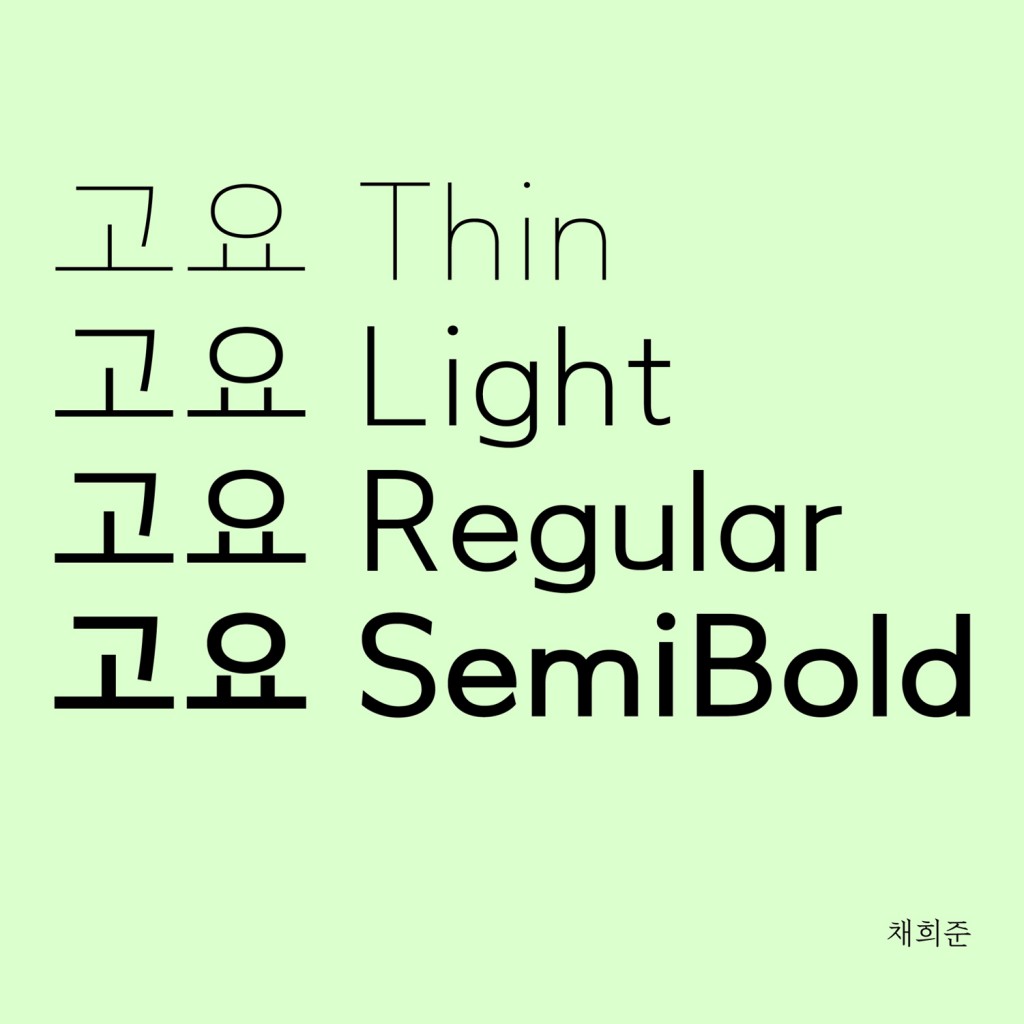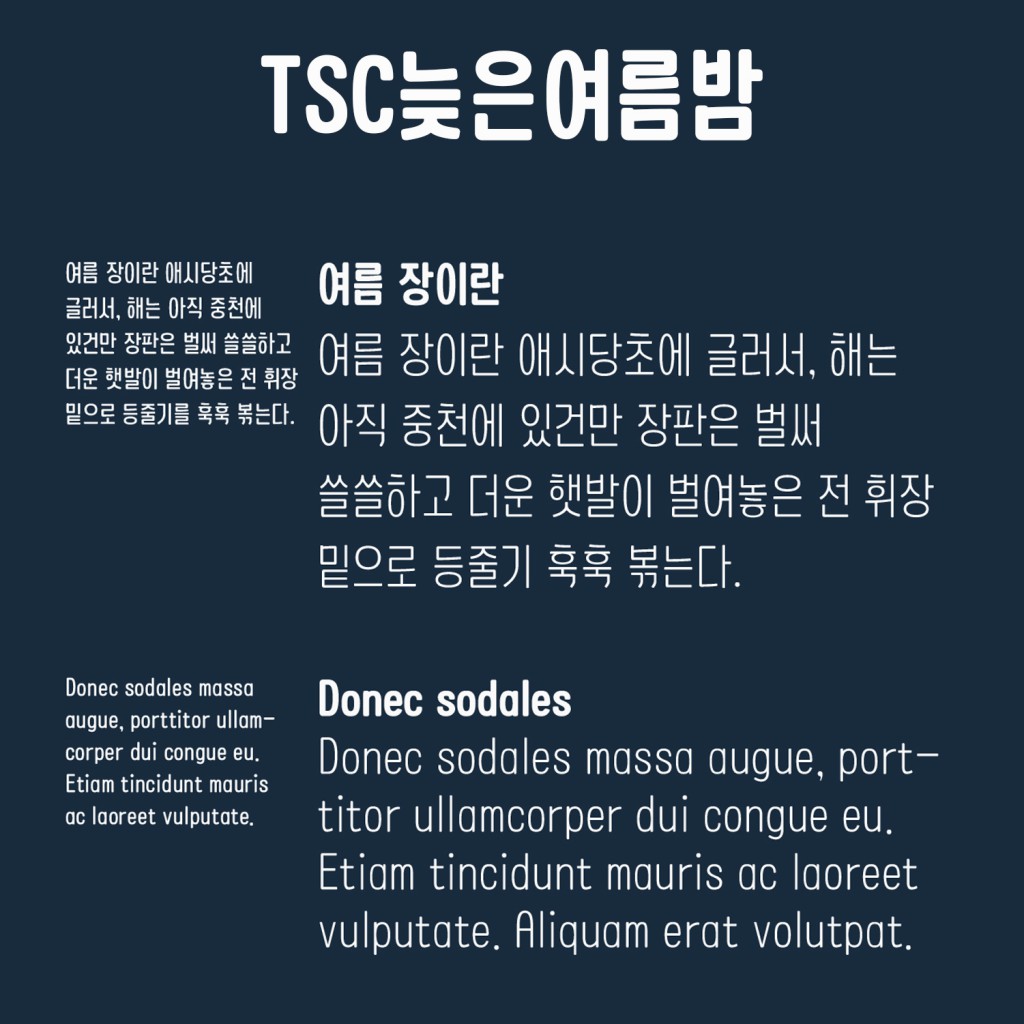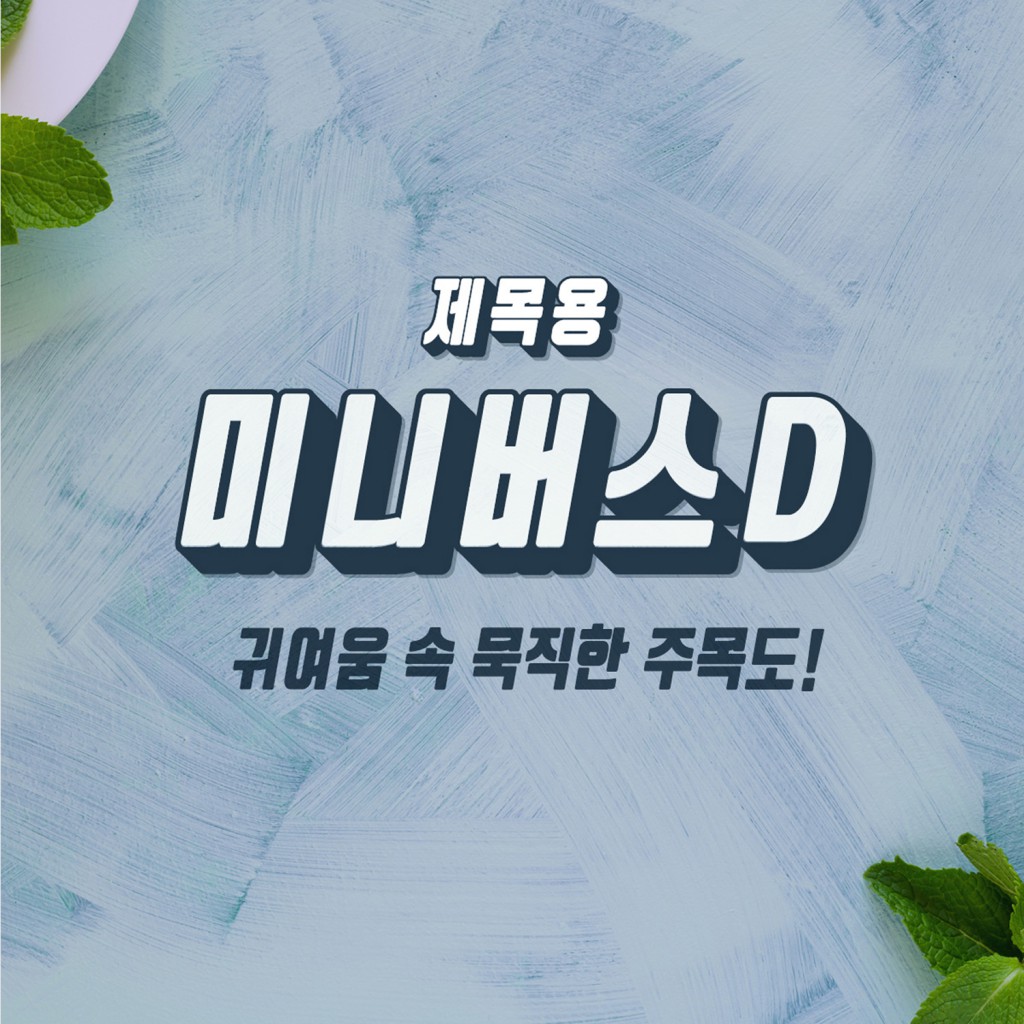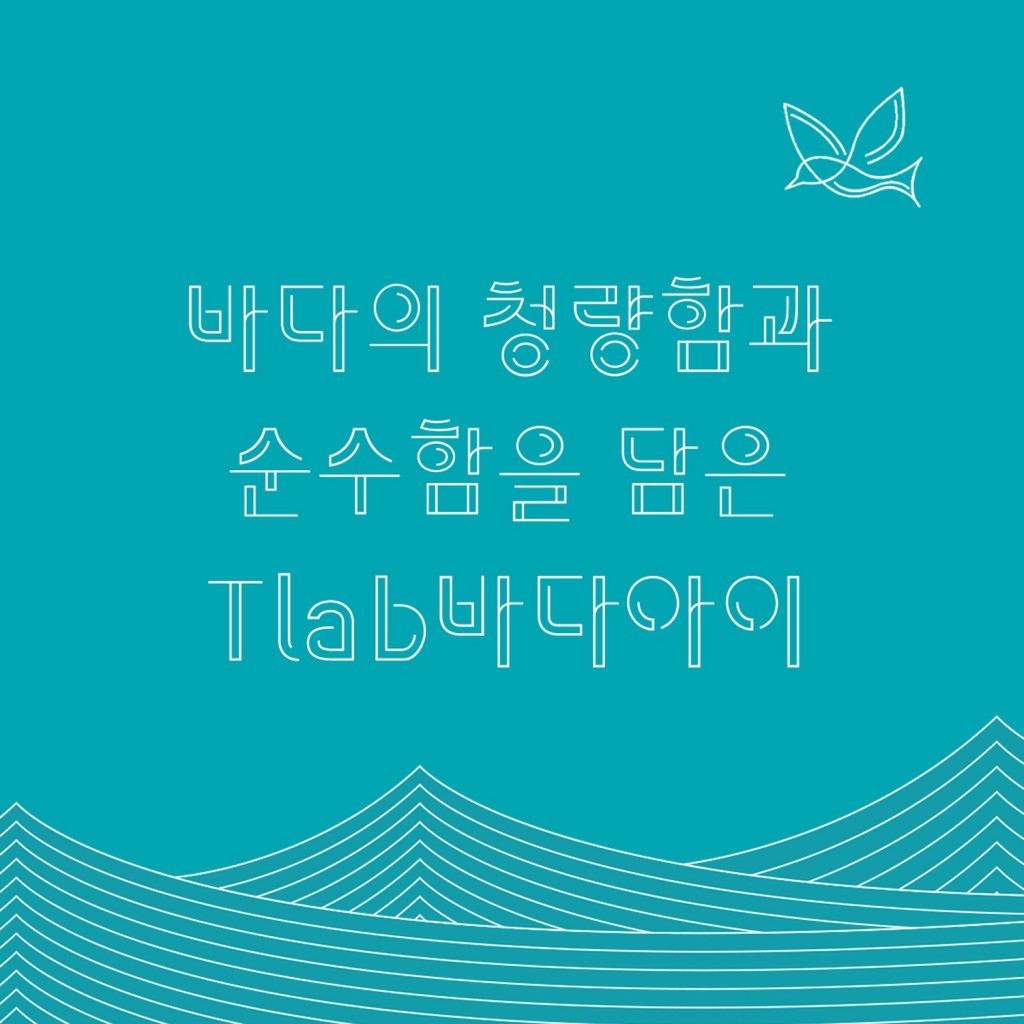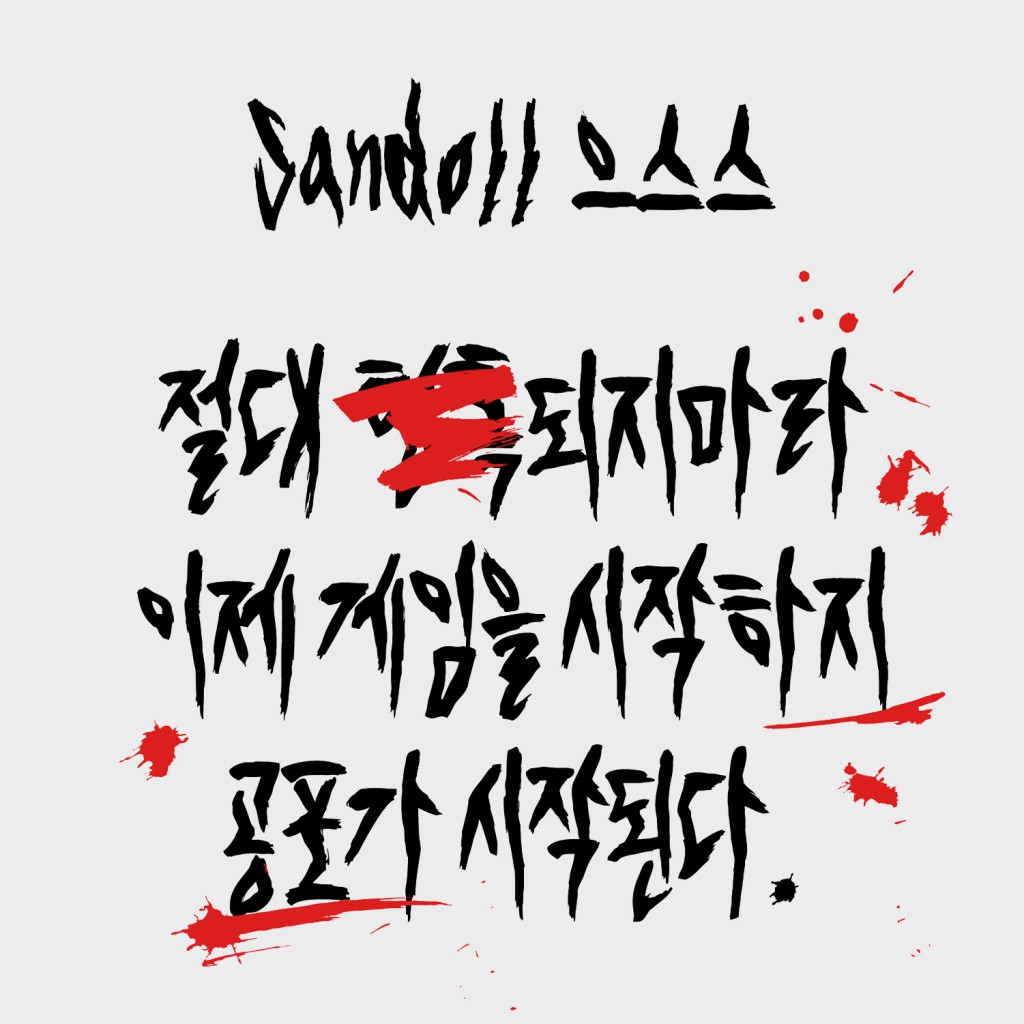
폰트에는 정답이 없어요. 어떤 폰트를 어디에 사용하느냐에 따라서 그 결과가 천차만별이거든요. 그래서 작업에 어울리는 폰트를 찾기 위해 이 폰트, 저 폰트 작업에 얹어가며 비교하기도 하고, 때로는 찾을 땐 없다가도 “이런 게 있었어?”라고 할 정도로 숨어있는 폰트들이 갑자기 보일 때도 있죠.
오늘은 더위와 장마가 공존하는 시기, 바로 7월에 사용하기 좋은 폰트 5개를 선별해 보았어요. 남들 다 쓰는 폰트는 지겹고, 그렇다고 딱히 뭘 써야할 지 모르겠을 때에는 아래 소개된 폰트들을 한 번 활용해보세요!
TSC늦은여름밤
이름에서부터 벌써 여름내음이 물씬 풍기죠? TSC늦은여름밤은 폭이 좁고 끝이 라운딩 처리 되어 있는 산세리프 계열의 폰트예요. 본격적인 여름이 시작되는 7월부터는 시원한 느낌을 내는 콘텐츠가 필요할 때가 많잖아요? 이럴 땐 모듈이 최대한 크고, 속공간이 널찍한 폰트가 제격이죠. 웨이트도 3개라 굵기에 대한 선택지도 있는 편이고요. 한글 11,172자를 모두 지원하기 때문에 표현의 자유도도 높습니다. ‘ㅁ’, ‘ㅂ’, ‘ㅅ’ 등에서 느낄 수 있는 재미요소들이 폰트를 너무 딱딱하지 않게 보여주기 때문에 캐주얼하게 사용하기에도 좋아요.
Tlab바다아이
Tlab바다아이는 바다의 청량함과 순수함을 그대로 옮긴 폰트예요. 바다의 수평선을 형상화 한 직선과 파도가 주는 유기적인 물결의 형태를 표현한 곡선이 조화를 이루고 있죠. 가독성을 고려한다면 본문으로 사용하긴 어렵겠지만 제목용으로는 더할 나위 없이 이 계절에 알맞은 폰트가 아닐까 싶어요. 선과 선으로 둘러쳐진 면은 작업자가 직접 색을 채울 수도 있어 개성있는 작업이 가능하죠. 각 획과 자소 사이의 빈 공간들로 시원한 바닷바람이 솔솔 불어올 것만 같은 폰트입니다.
Sandoll 으스스
납량특집 만들어야 하는 분들 모두 주목하세요! 구름레터에 폰트 제작기로도 소개한 적이 있는 Sandoll 으스스는 작정하고 여름을 겨냥해 만든 폰트입니다. 이름에서 느낄 수 있듯이 공포, 호러와 같은 느낌의 콘텐츠를 제작할 때 사용하기 좋죠. 한글 폰트는 영문 폰트에 비해 역사가 짧다보니 항상 디자인 할 때마다 다양한 갈래의 디자인이 부족한 것 같다는 단점이 있었는데요. 이렇게 컨셉이 분명한 폰트들이 계속해서 나와주면 너무 좋을 것 같아요. 함께 출시된 Sandoll 끼기긱도 추천합니다.
고요
고요는 여유로운 공간과 자간이 특징인 산세리프 서체입니다. 인상이 굉장히 서정적이라 굳이 비유를 하자면 여름철 놀러간 시골 할머니댁 마당같은 폰트랄까요? 평상에 둘러 앉아먹는 시원한 수박도 떠오르고요. 그 앞에는 시냇물도 졸졸 흐르고, 멀리 뒷동산에서는 매미소리도 은근히 들려오는 그런 느낌이죠. 정제된 타이포그라피가 필요하긴 한데, 그 속에서도 약간의 계절감은 챙겨가고 싶다면 고요를 사용해보세요.
Rix미니버스D
이벤트 배너나 유튜브 썸네일로 쓰기 너무 좋은 폰트를 하나 찾았어요. 바로 Rix미니버스D인데요. 쉐도우도 이미 들어가 있어서 포토샵으로 이리저리 만질 필요도 없이 타이핑만 해도 눈에 띄는 타이포그라피가 완성됩니다. 직사각형 꽉찬 모듈에, 기울기까지 적용되어 있어서 타이틀에 쓰면 딱인 폰트죠. 타이틀용 서체임에도 11,172자를 모두 지원하는 점도 좋네요.